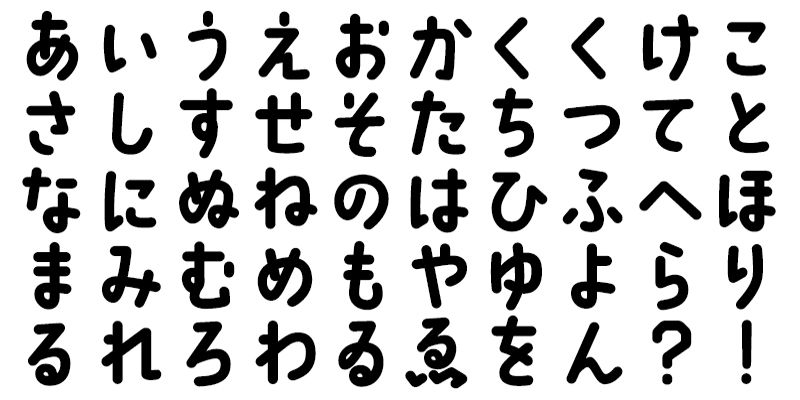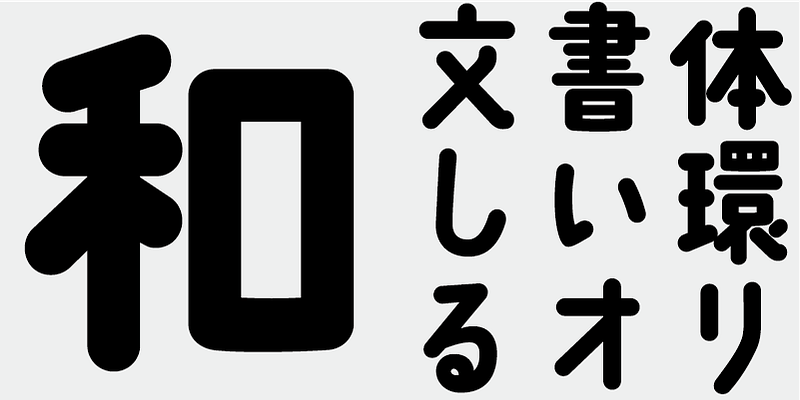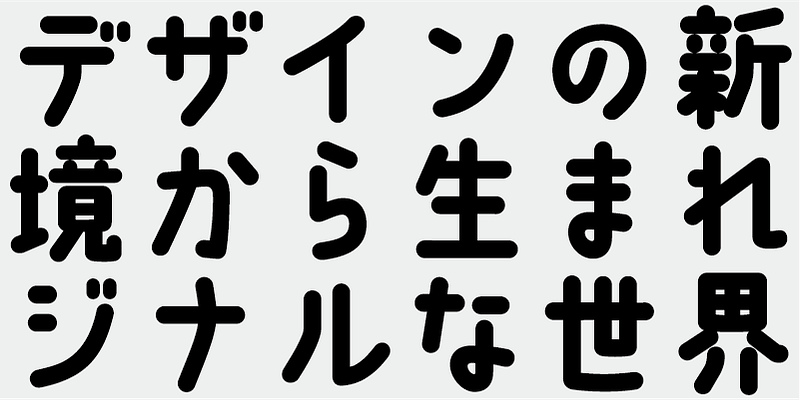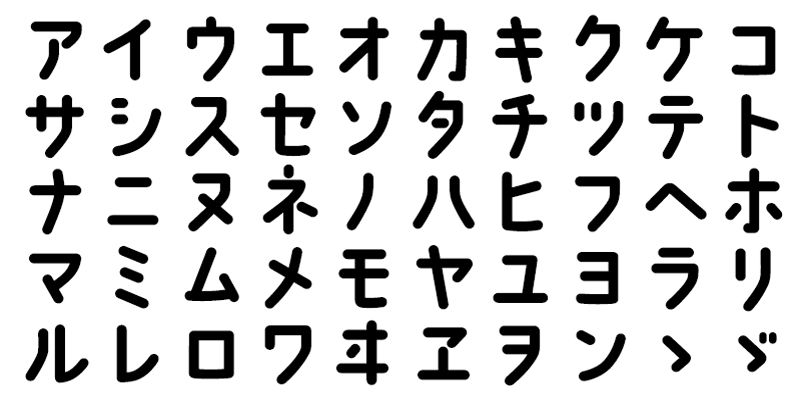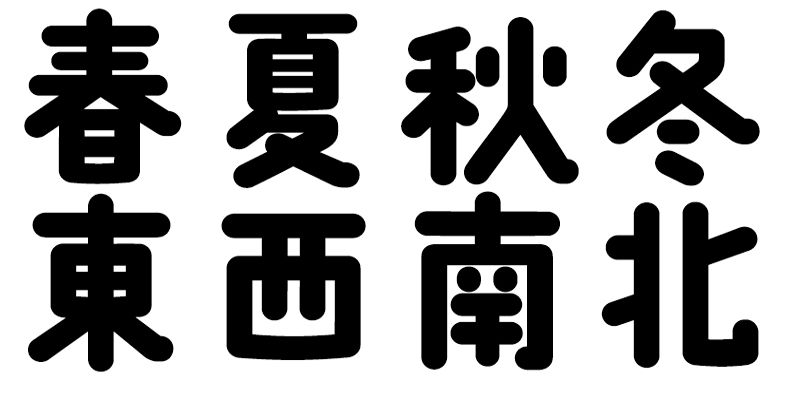
言葉を伝える手段としての文字。その背景にある感動、感謝、思い出など一緒に伝えたい。そんな想いを表現しました。「こころ」3 書体の最も太いタイプです。
このフォントには、新聞社、出版社、国語研究所等の使用頻度表から選んだ上位 1,000 個の漢字に加え、206 個の両仮名および約物が含まれています。